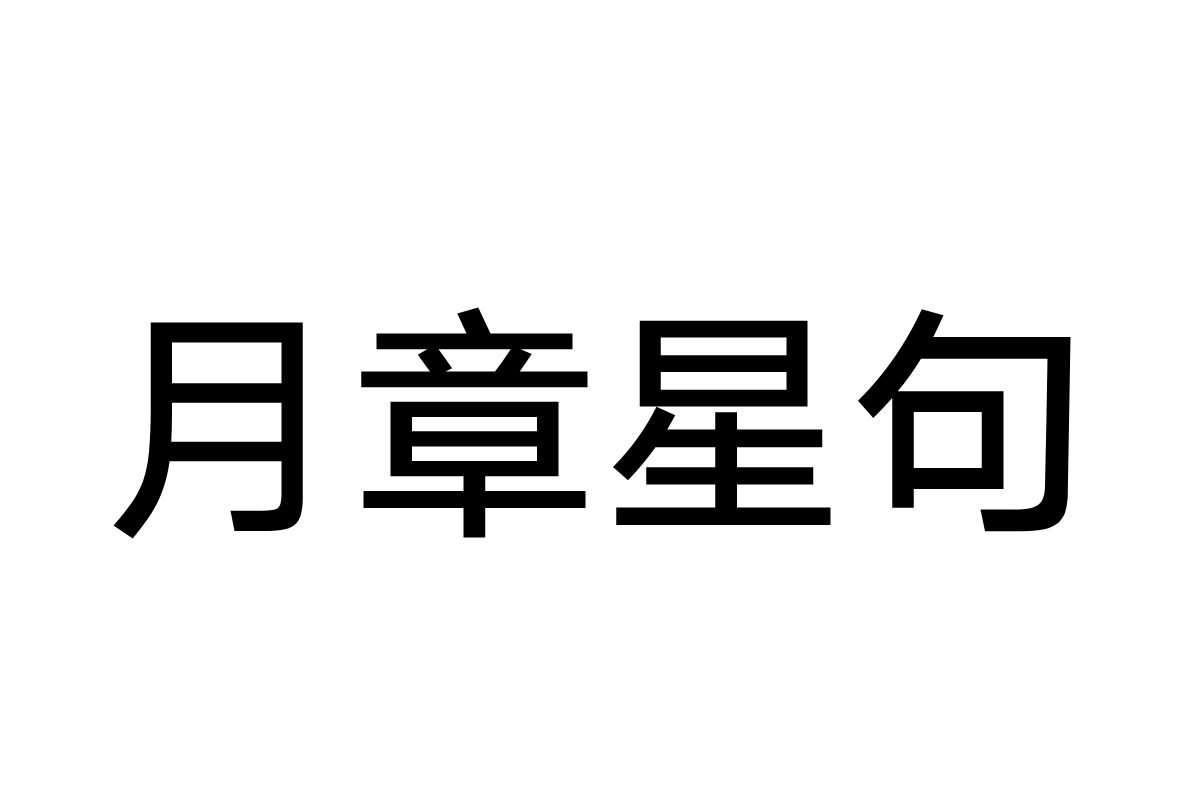
汉仪旗黑-60是一款专为中文书写设计的字体,具有独特的风格和特点。这款字体的特点是笔画粗细均匀,字形结构紧凑,线条流畅,给人一种简洁、大方的感觉。同时,它的笔触力度适中,既适合快速书写,又适合细致描绘,满足了不同用户的需求。
此外,汉仪旗黑-60还具有一定的可读性,字体大小适中,易于阅读,无论是在正式场合还是在日常生活中都能使用。总的来说,汉仪旗黑-60是一款实用性强、风格独特的字体,值得推荐给需要使用中文字体的用户。
汉仪旗黑-60